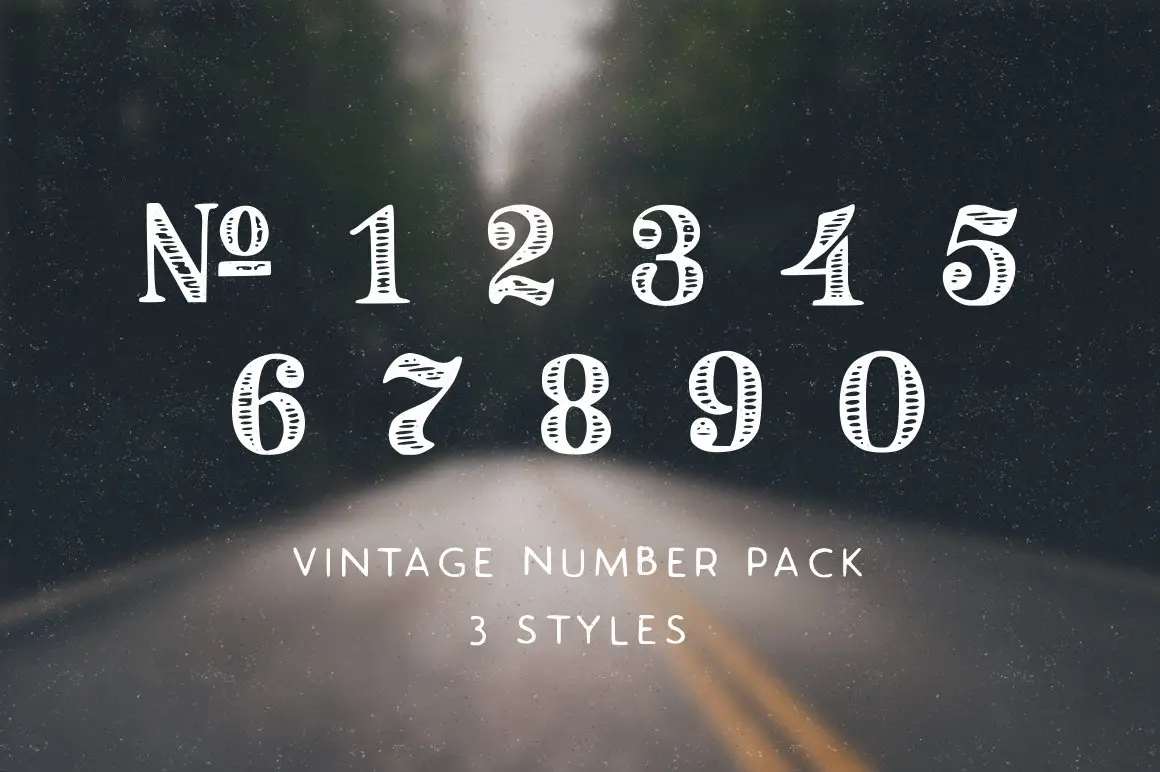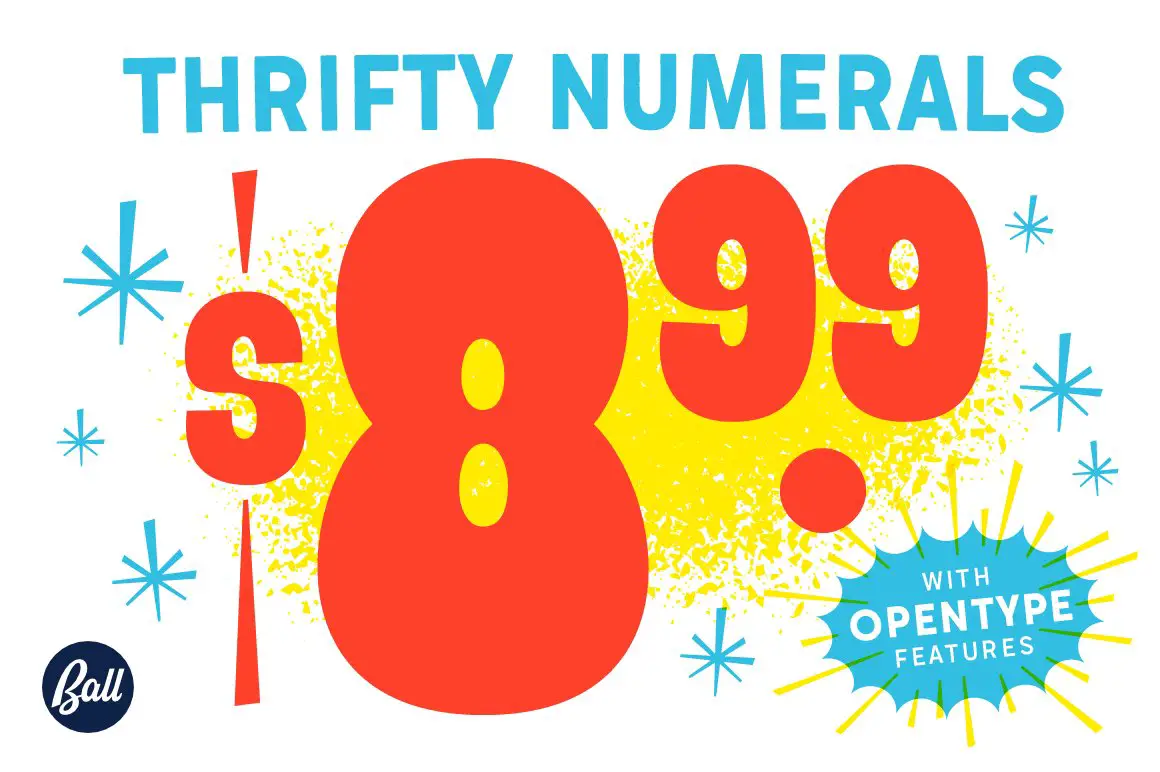
25 Font Angka Terbaik (Gratis & Pro)
Diterbitkan: 2023-03-26Jika Anda pernah menemukan diri Anda mencari font angka yang sempurna? Tidak ada bedanya apakah itu untuk sebuah proyek atau hanya untuk menyempurnakan desain Anda, menemukan yang sempurna bisa menjadi tantangan tersendiri. Bagaimana Anda tahu font mana yang terbaik untuk kebutuhan Anda?
25 Font Angka Terbaik (Gratis & Premium) menawarkan pilihan font yang luar biasa untuk setiap proyek desain. Posting blog ini mencakup semua basis; dari nomor klasik hingga font modern dan dekoratif, semuanya dirancang untuk menginspirasi kreativitas.
Kami telah dengan hati-hati memilih font gratis dan premium yang telah diperiksa, dengan fokus pada kegunaan dan kualitas. Setiap pemilihan font telah diuji kompatibilitasnya untuk berbagai perangkat dan perangkat.
Anda dapat menemukan font yang sempurna untuk proyek Anda apakah Anda seorang desainer grafis yang mencari font angka yang tepat atau pemilik bisnis yang mencoba menambahkan sentuhan bakat pada branding mereka. Lihat koleksi font gratis dan premium kami yang pasti akan membuat desain Anda menonjol!
Font Angka Premium Terbaik
Musim panas 0f 76
Number Fonts adalah solusi sempurna untuk desainer grafis yang ingin menambahkan sentuhan retro pada desain mereka. Font, yang disebut Summer of '76, dibuat dengan mempertimbangkan estetika tahun 70-an, menjadikannya bagus untuk header, serta blok teks.
Saya suka tampilan font ini, dan menurut saya jelas bahwa begitu banyak pekerjaan telah dilakukan untuk membuatnya, termasuk perhatian terhadap detail seperti desain multi-garis dan karakteristik uniknya. Dan yang terbaik, mudah digunakan, dengan proses instalasi sederhana yang hanya membutuhkan beberapa menit untuk menyelesaikannya.
Font ini hadir dengan paket grafik vektor Musim Panas 1976, namun dapat digunakan secara terpisah juga. Apa pun jenis proyek yang sedang Anda kerjakan, font ini akan membantu Anda membuat desain menarik yang menonjol dari yang lain.
Nomor Kamar Didone
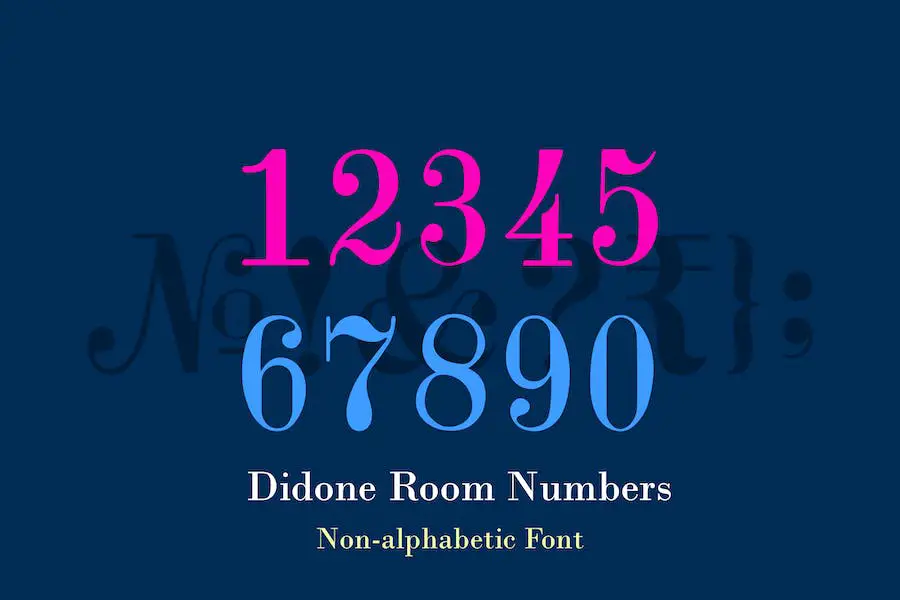
'Didone Room Numbers' adalah font serif bergaya dan modern yang berfokus pada simbol numerik. Itu bagian dari keluarga jenis huruf Didone, yang sempurna untuk tujuan tampilan. Font ini memiliki nuansa unik yang terinspirasi dari nomor kamar hotel tulisan tangan dari Wina, Austria.
Font ini cocok untuk berbagai macam proyek desain, termasuk logo, judul, label, kartu ucapan, dan sebagainya, yang semuanya dapat digunakan dengan sukses dalam font ini.
Memberikan kehadiran yang kuat melalui gayanya yang berani sambil mempertahankan kelas, Blok Teks Satu Langkah menyediakan cara mudah untuk membuat desain yang menarik. Selain itu, tepiannya yang bersih dan tajam membuatnya sangat mudah dibaca, sehingga memberikan pengalaman membaca yang mudah.
Bukan tipe saya
Font mesin tik 'Bukan Tipe Saya' dibuat dari mesin tik kurir Oliver yang dibeli di pasar barang antik dan memiliki 3 kemungkinan alternatif untuk setiap karakter; itu salah satu font mesin tik paling detail yang dapat Anda temukan di sini di Pasar Kreatif.
Tidak ada keraguan bahwa font ini akan menjadi pilihan yang sempurna untuk desainer mana pun yang ingin membuat desain seperti mesin tik di proyek berikutnya. Ini memiliki nuansa kuno dan retro yang dikombinasikan dengan sedikit kekotoran di dalamnya.
Selain huruf besar & huruf kecil dengan tiga alternatif, angka dengan tiga alternatif, tanda baca & simbol dasar, font dilengkapi dengan banyak detail, seperti alternatif kontekstual, yang akan membantu Anda mendapatkan tampilan mesin tik yang berdampak nyata.
Voni 43
'Vonique 43' adalah font unik dan glamor yang akan membuat logo apa pun langsung menonjol. Ini angsuran ketiga dari keluarga Vonique, menampilkan banyak karakter warisan dengan gaya yang ramping dan seksi.
Huruf kecilnya melengkung dengan elegan, dengan turunan hampir tidak ada untuk mencocokkan tinggi huruf kapital. Meskipun tidak dirancang untuk penggunaan teks sehari-hari, font ini bagus untuk merek mewah, lini pakaian, atau butik. Ini termasuk Basic Latin, Extended Latin, Cyrillic, Greek, tanda baca, alternatif, dan kerning.
Di antara banyak alasan mengapa font ini menonjol adalah perhatiannya terhadap detail. Setiap karakter telah dibuat dengan hati-hati sehingga menarik dan bergaya. Tidak ada keturunan sama sekali dan lekukannya mulus.
Itu bersatu untuk membuat font yang benar-benar menakjubkan yang akan menambah sentuhan mewah pada logo apa pun.
Nomor Clement
'Clement Numbers' adalah buku spesimen tipe unik yang diterbitkan oleh Fonderie Clement pada tahun 1838. Set ini mencakup 10 font angka vintage yang cantik, masing-masing dengan gaya dan kepribadian tersendiri.
Nomor 5 memiliki bagian atas yang sangat menarik yang pasti menonjol dari keramaian, sedangkan nomor 2 menawarkan pusaran spiral yang menyenangkan. Nomor 4 adalah kelas murni, sedangkan nomor 8 adalah sentuhan yang lebih lebar dari yang lain, dengan penghitung yang lebih besar.